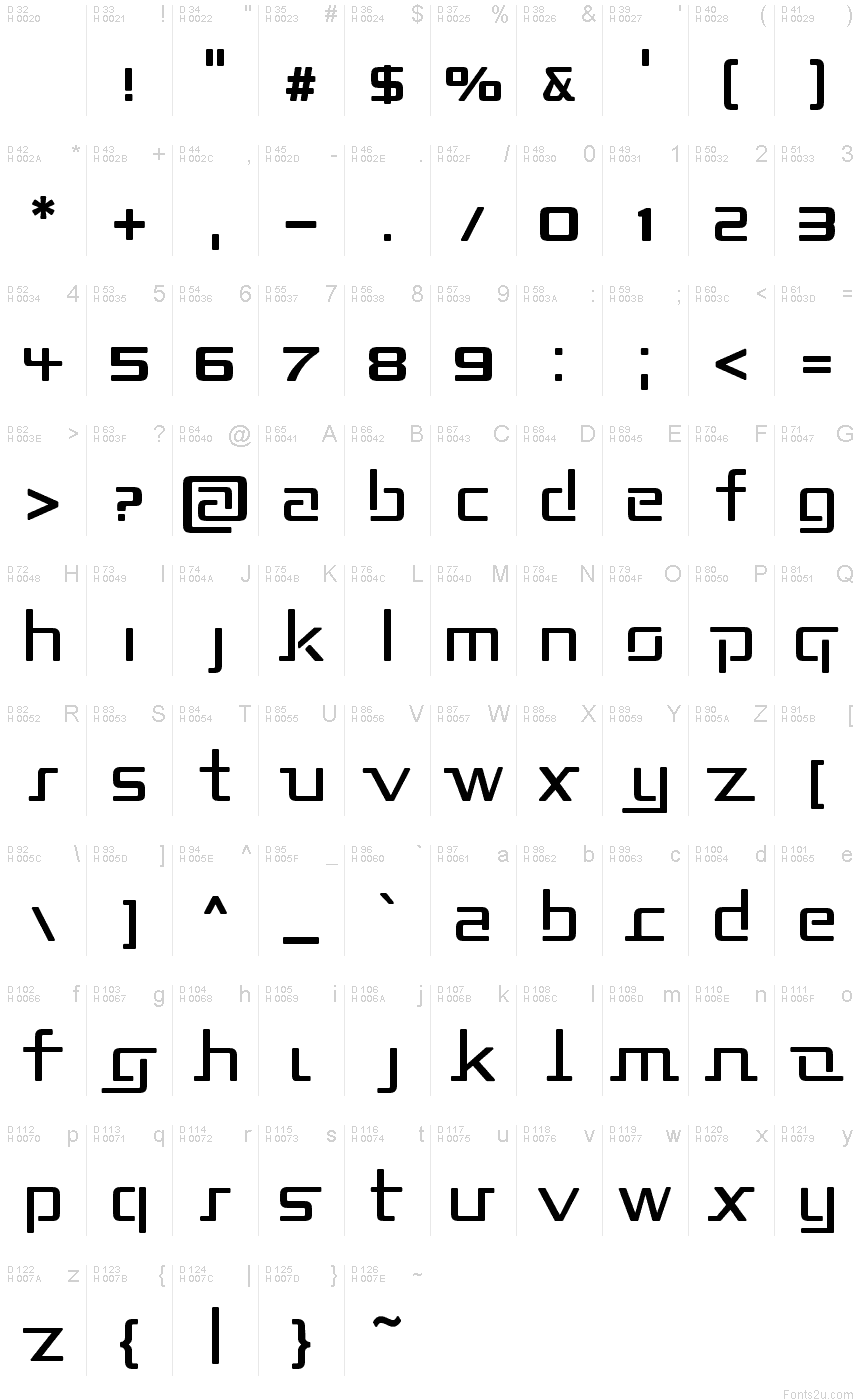
Republika II von Apostrophe ist eine kostenlose modulare Techno-Display-Schrift mit einem eleganten, schaltkreisartigen Rhythmus. Die Buchstaben sind aus quadratischen Kurven und stumpfen Monoline-Strichen aufgebaut, was dem Alphabet eine kompakte, futuristische Anmutung verleiht – irgendwo zwischen frühem Digital-Branding und moderner urbaner Beschilderung.
Diese kostenlose Schrift eignet sich hervorragend für Musik-Flyer, Poster-Überschriften, App-Branding, Titelkarten und Verpackungen, bei denen eine klare Sci-Fi-Note den Ton angibt. Da die Formen so präzise ineinandergreifen und die abgerundeten rechten Winkel wiederholen, funktioniert sie auch bestens für kurze Logos, Cover-Lines und Wordmarks, die eine kontrollierte, synthetische Ästhetik erfordern.
Republika II